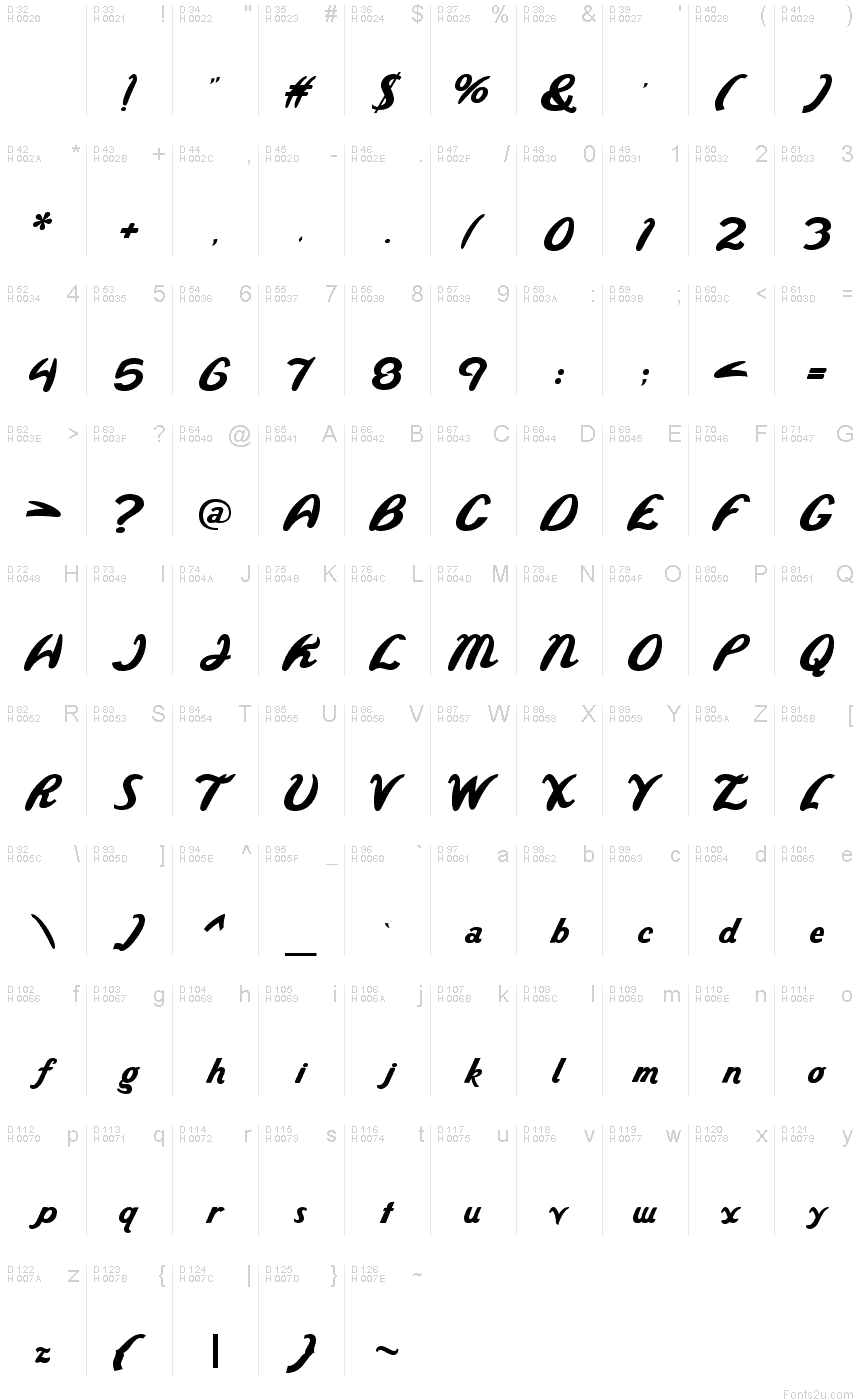
Wild Ride, darmowy krój brush autorstwa Michaela Hagemanna, mocno stawia na styl hot-rod, oferując szerokie, zamaszyste pociągnięcia i szybki, ręcznie malowany charakter. Litery łączą się w gęste, błyszczące krzywe z ostrymi złączeniami i długim, wznoszącym się ruchem, sprawiając wrażenie, jakby cały wyraz powstał za jednym zamachem.
Świetnie sprawdza się na nagłówkach plakatów, okładkach płyt, grafikach na koszulki, szkicach logo i ulotkach eventowych – wszędzie tam, gdzie darmowy font ma mieć w sobie więcej dynamiki niż gładkiego wykończenia. Użyj go do krótkich tytułów, tekstów na okładkach lub wyrazistego logotypu, gdy chcesz uzyskać efekt odręcznego, nieco niepokornego napisu, szczególnie w projektach w stylu retro, rockabilly czy surf.